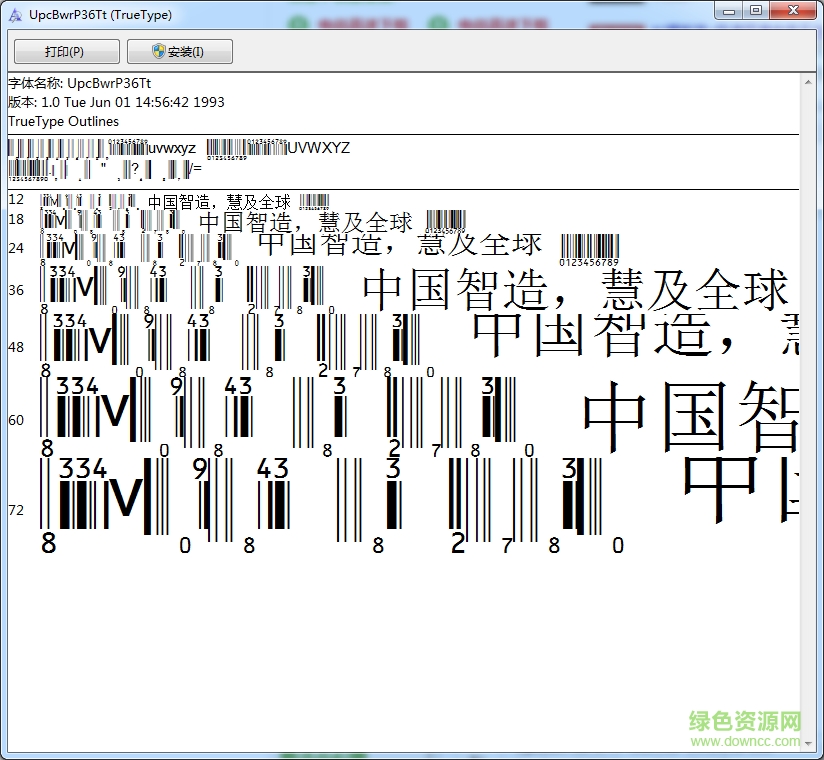
UpcBwrP36Tt是一款非常實(shí)用的條形碼字體軟件,以條形顯示對(duì)應(yīng)的中文字體,使用便捷獨(dú)具個(gè)性。快來綠色資源網(wǎng)下載體驗(yàn)吧!
UpcBwrP36Tt ttf(條型碼字體),可以將輸入的數(shù)學(xué)或字母轉(zhuǎn)換成帶有條型碼的數(shù)字和字母。